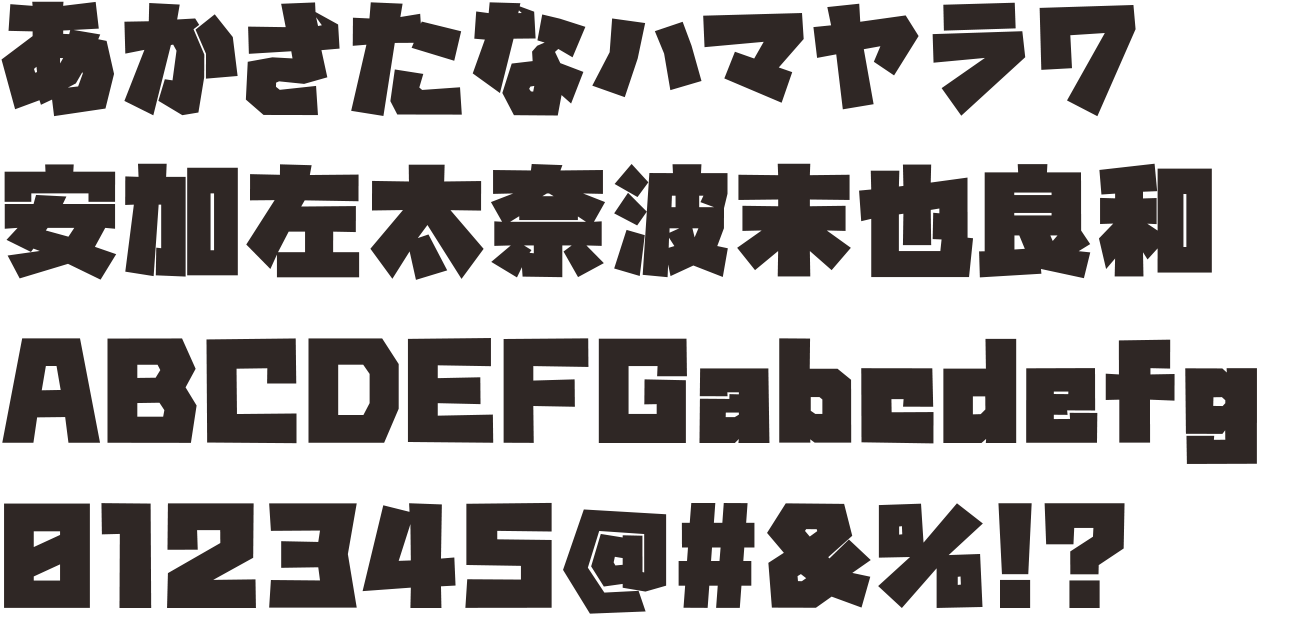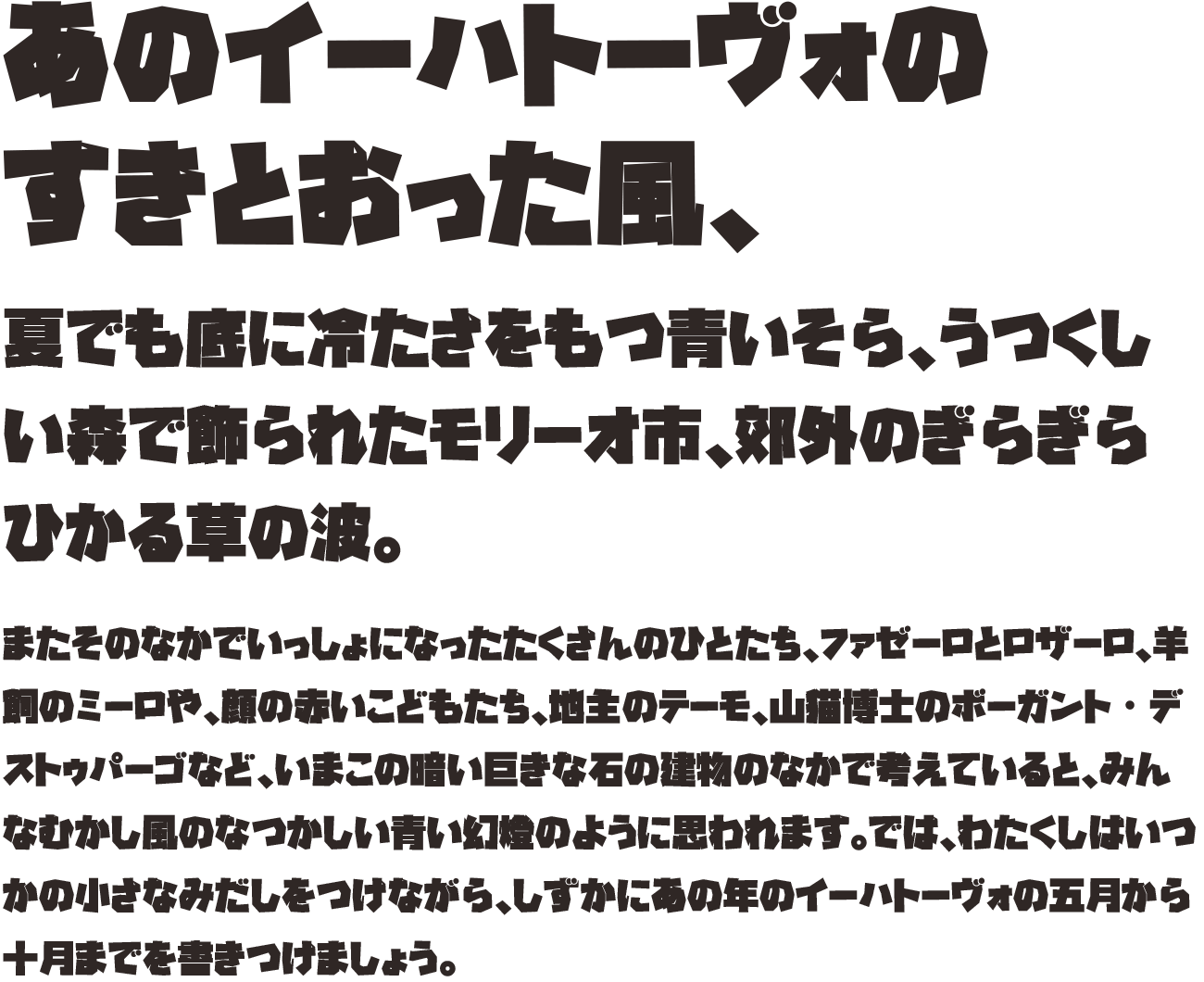
キルゴU かなO
漫画「キルミーベイベー」のタイトルロゴに似せて制作されたデザインフォント。超極太で目立つ上に漢字も使えるので、とくに動画のサムネやテロップにおすすめ!
直線的でロゴに近い「NA」のほか、かなにゴツゴツとした力強さをもたせた「NB」「O」も収録されています。
キルゴU かなOの組見本